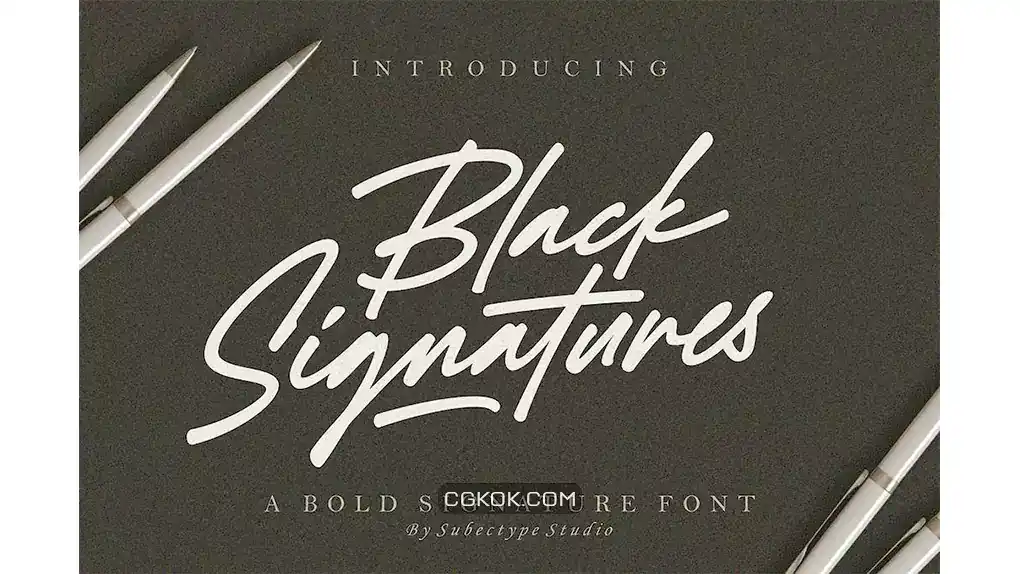
دانلود فونت انگلیسی به سبک امضا Black Signatures – Signature Font
فونت انگلیسی به سبک امضا Black Signatures – Signature Font : این مجموعه شامل فونت انگلیسی دست نویس مدرن است که برای امضا، لوگو، واترمارک استودیو عکاسی، کارت عروسی و غیره مناسب میباشد.
• فضا بین حروف: معمولی، متراکم، با فاصله